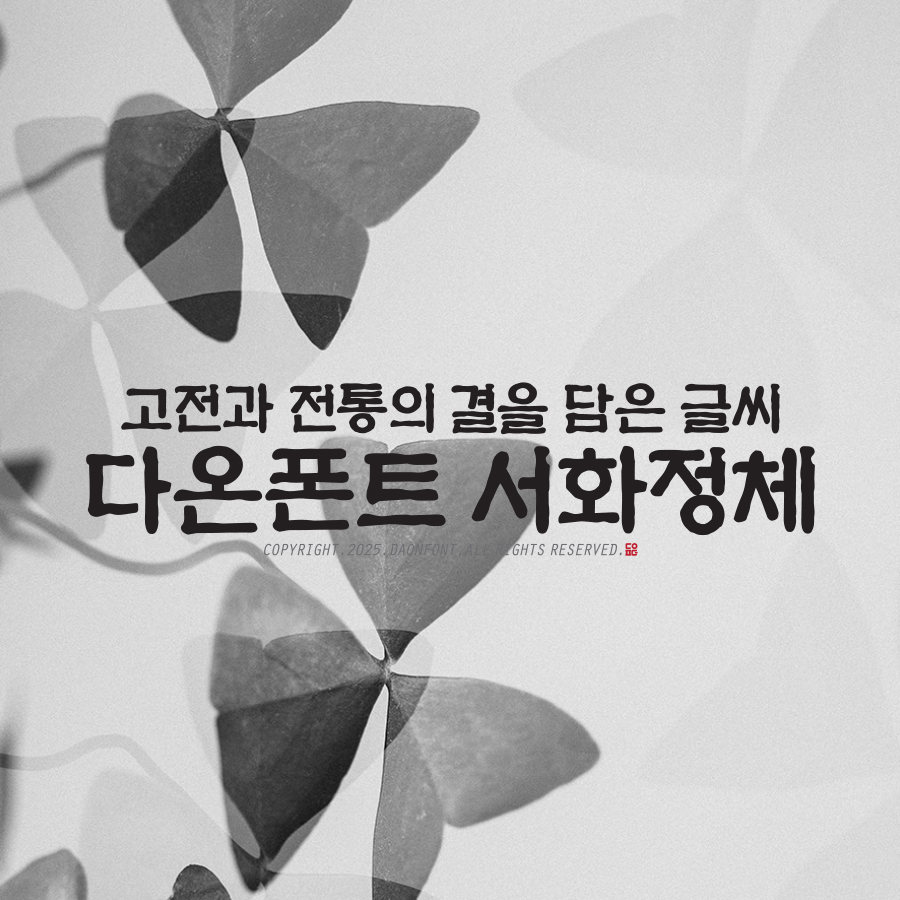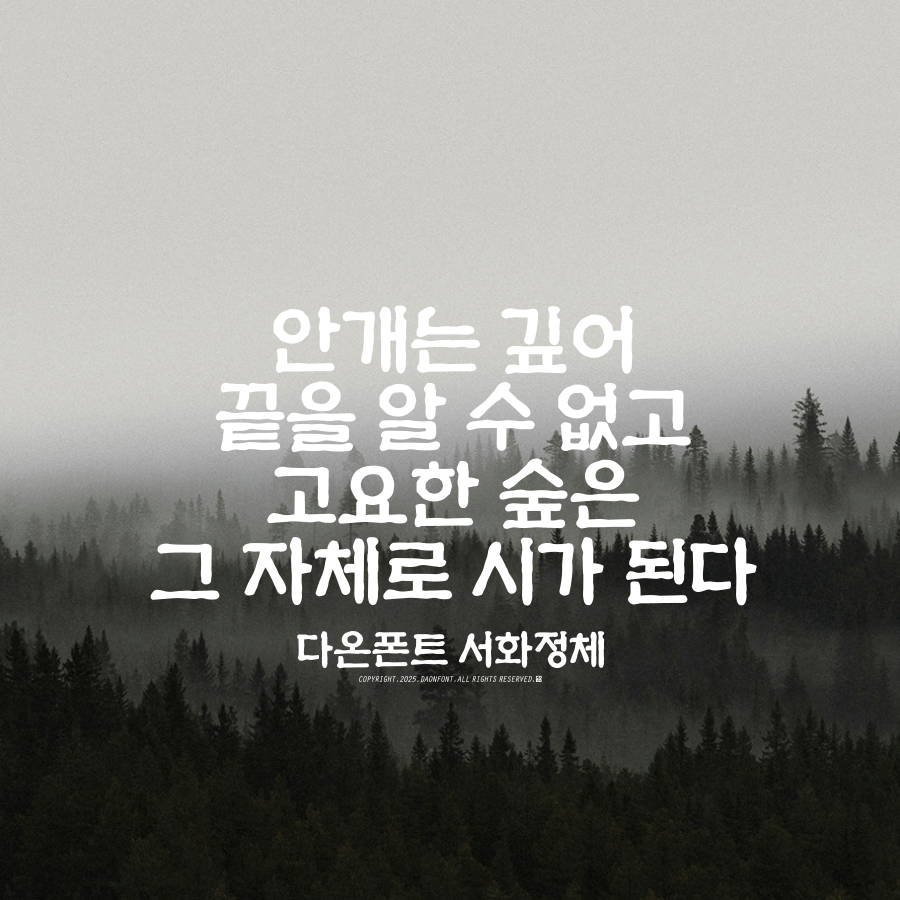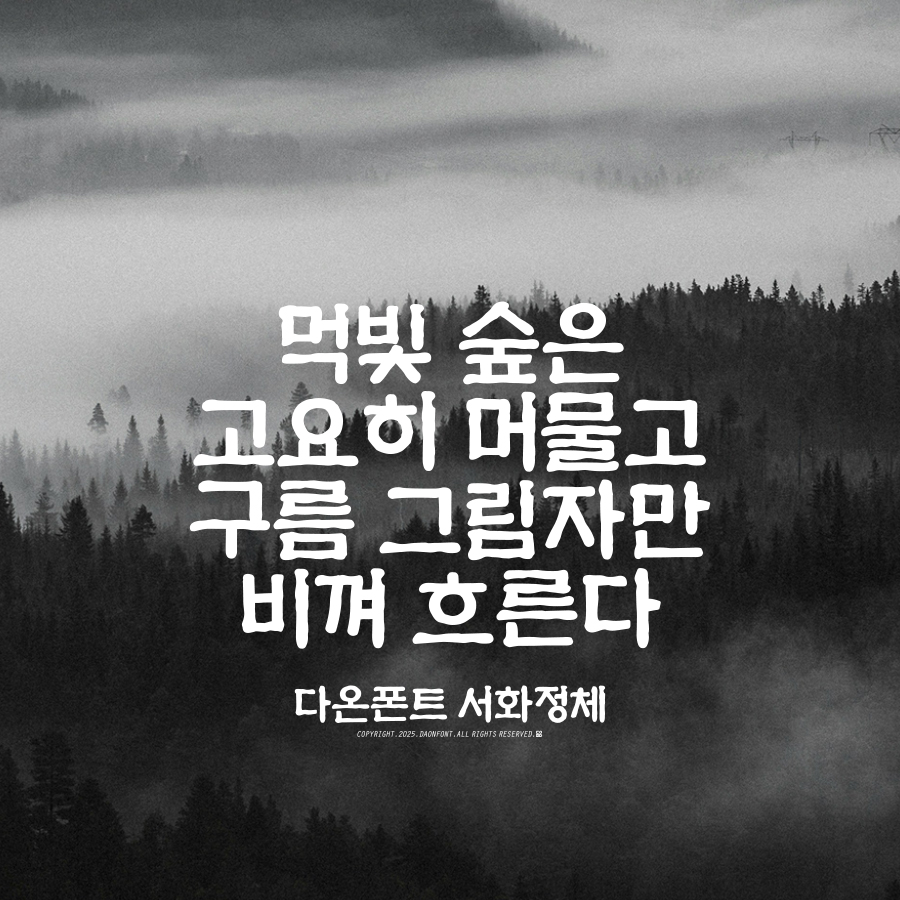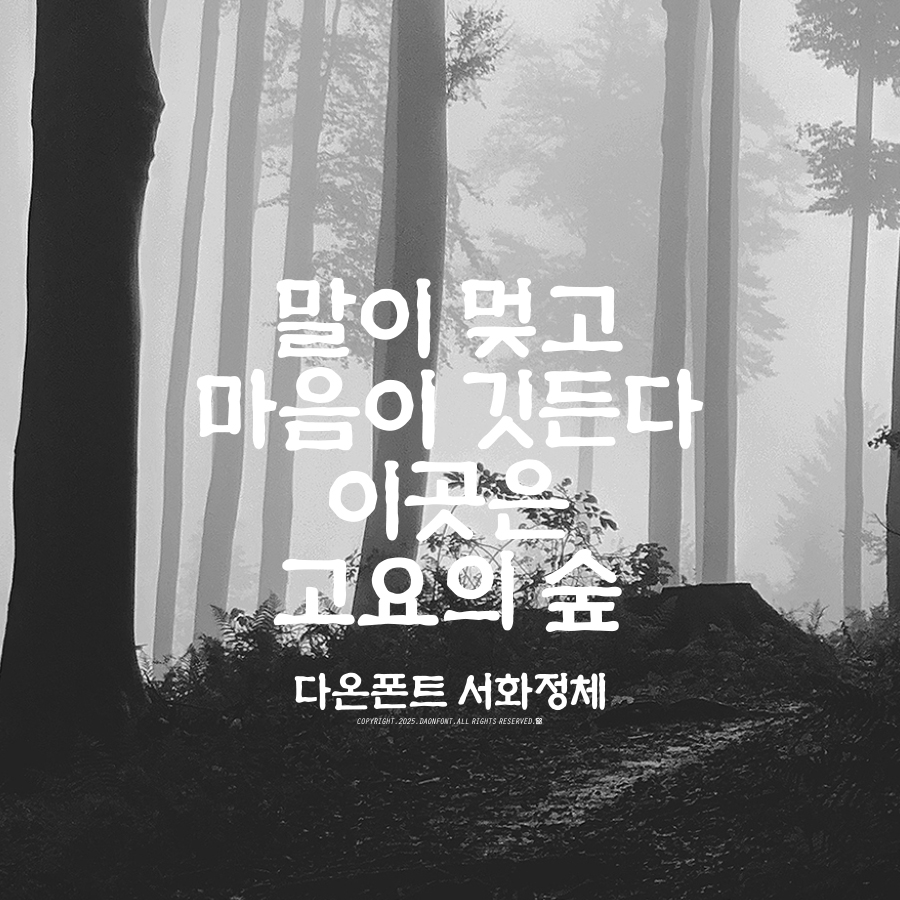
다온폰트 신서체 "서화정체" 제작 안내
고전의 깊이와 전통의 온기를 담은 서체,
다온폰트의 신서체 서화정체를 소개합니다.
한 획, 한 자에 담긴 붓의 결과 정신을 바탕으로
고전 서예의 품격을 현대 타이포그래피로 재해석한 서화정체는
시간의 아름다움을 머금은 또 하나의 글꼴로 완성될 예정입니다.